台北的设计师Chen Chiao-Yu
跟大家分享一个来自台北的设计师Chen Chiao-Yu几年前所作品《字以为释-成语实验室计画》。以成语为主题的字体创作,将文字结合文字创造出新字或者结合符号,完成一系列的创作。
以下有67个字体设计,同时也是67个成语,从以下图中你能认出几个?
画蛇添足
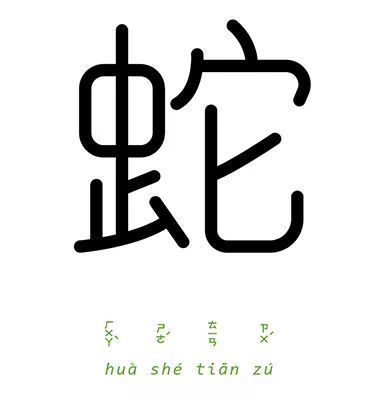
如虎添翼
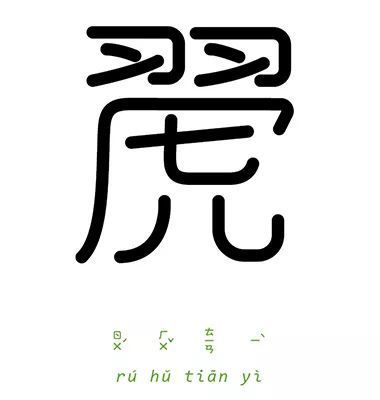
苦中作乐
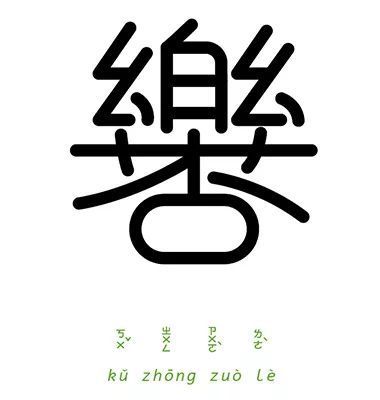
以牙还牙
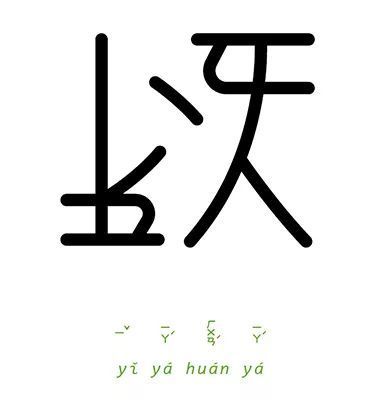
两小无猜
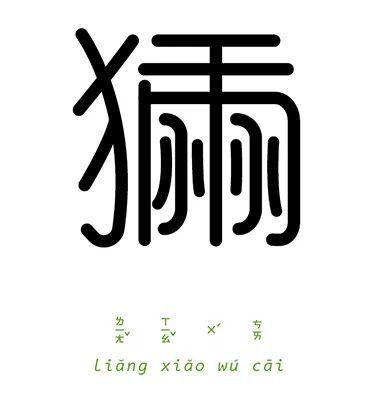
胸有成竹
羊入虎口
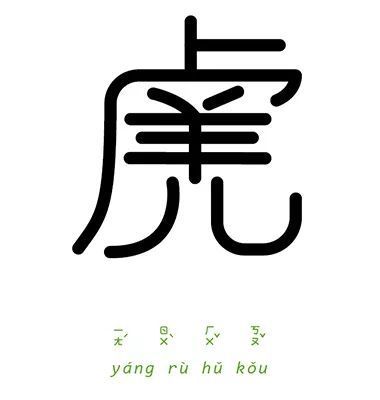
九牛二虎
祸从口出
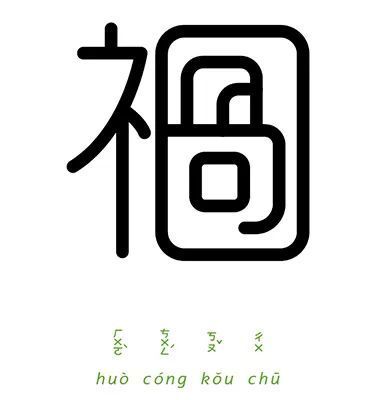
自以为是
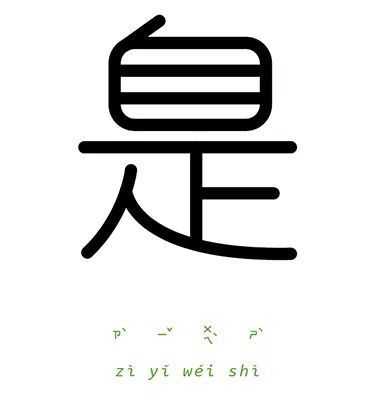
伯仲之间
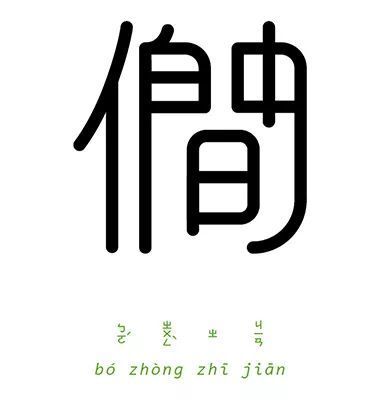
若有若无
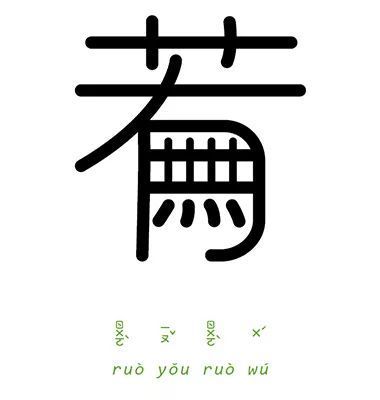
牛头马面
恨之入骨
骨肉相连
改头换面
上山下海
耿耿于怀
一石二鸟
无中生有
笼中之鸟
开卷有益
偷天换日
笑里藏刀
待字闺中
话中有话
百感交集
青出于蓝
积少成多
雪上加霜
一手遮天
囊空如洗
人各有志
官官相护
隔墙有耳
崭露头角
小鸟依人
火上加油
断袖之癖
祸不单行
出口成章
不约而同
喋喋不休
高不可攀
一笔勾销
虚有其表
对症下药
雾里看花
甜言蜜语
一哄而散
黑白分明
胸无点墨
风前残烛
虚左以待
正中下怀
倾盆大雨
祸从口出
蝇头小利
双管齐下
勾心斗角
可圈可点
捕风捉影
心猿意马
开源节流
隔行如隔山
言而无信
刮目相看